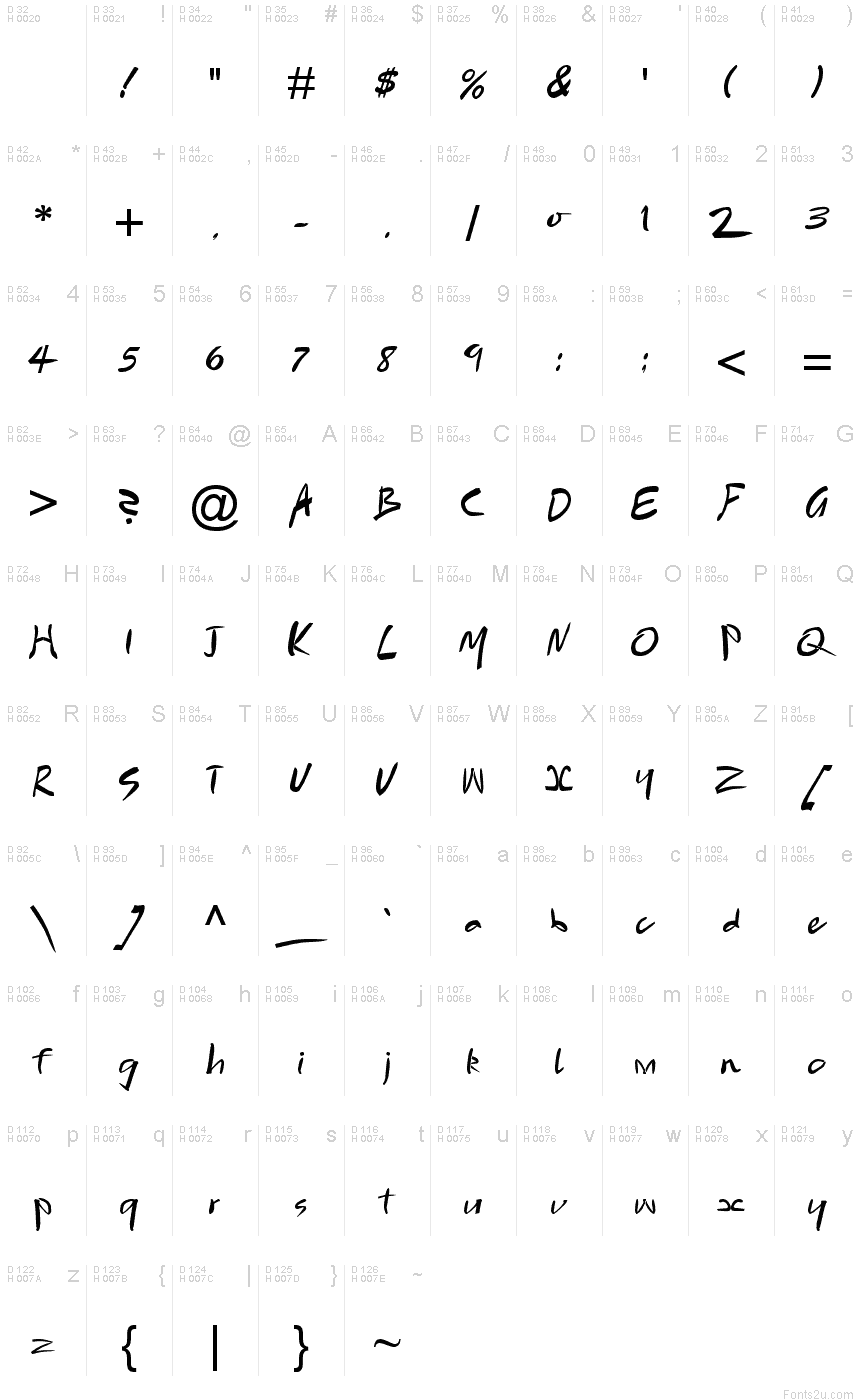
Sydney 2000 autorstwa Caleba Tivendale'a to darmowy krój pisma typu brush script z szybkimi, skośnymi pociągnięciami i nierównomiernym naciskiem ręcznie malowanych liter. Jego długie zamaszyste ruchy i ostre zakręty sprawiają, że ma on bezpośredni, sportowy charakter.
Akcja i kultura młodzieżowa naturalnie pasują do tego żywego, gesturalnego stylu, szczególnie na plakatach sportowych, które opierają się na ruchu i rywalizacji. Szeroki ruch pędzla nadaje również gadżetom koncertowym i okładkom płyt pilność szybko namalowanego szyldu, zachowując wystarczającą nieregularność, by wydawać się osobistym, a nie fabrycznym. W innym kontekście jego odręczna linia może kształtować codzienne opakowania żywności i identyfikację wizualną kawiarni, gdzie zamaszyste formy nawiązują do liter pisanych markerem na menu i szyldach lad.